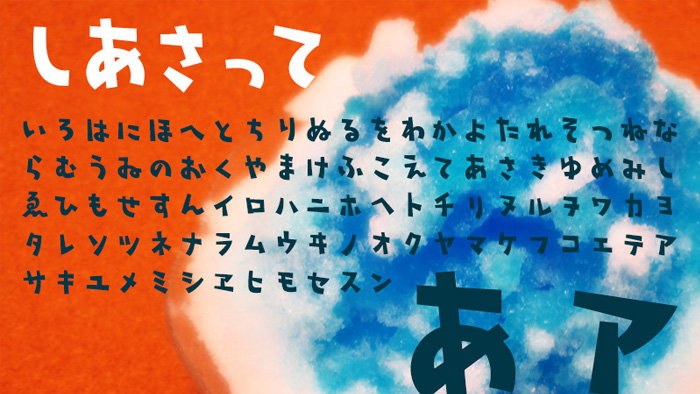
しあさって
しあさってフォントは、色んな方向に向いているようなユニークなフォントで、やる気がありそうでなさそうな程良いゆるさと、どことなくレトロ感も特徴です。ひらがな・カタカナのみのフォントです。
ひらがなフォントなので、漢字は収録されていないですが、ひらがなのロゴなどで使うととっても可愛いロゴタイトルができそうです。
文章で使いたい場合は、他のフォントの漢字と混植文字として使うのもアリですね。配布サイトで混植文字のサンプルがあるのでぜひ参考にしてみてください。